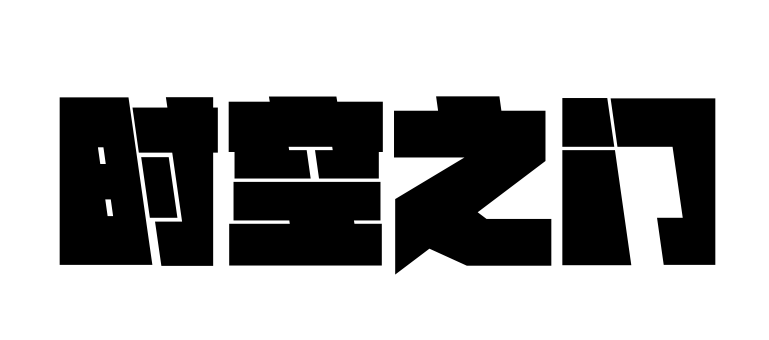
爆火全网的逆反差字体,给你极致的视觉体验
逆反差字体
逆反差字体是西文字体设计所衍生出来的概念,强烈的横向视觉。它的出现不仅带来了一场字体设计的视觉革命,也是对视觉设计规律的创新和突破。这种小众但是却很时髦的设计风格,也适用于用在酸性设计作品中。今天带来的1款逆反差字体,相信看完你一定会喜欢的。
独特的变形字体——励字飞行黑简。字形方正、中宫宽博、起收笔平直,将左部字体重心向左倾斜,赋予字体独特的视觉张力,整体视觉形象模仿宇宙飞船的飞行状态。